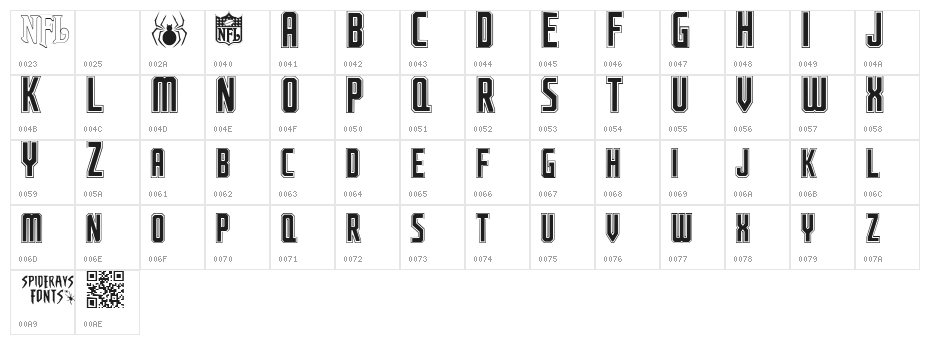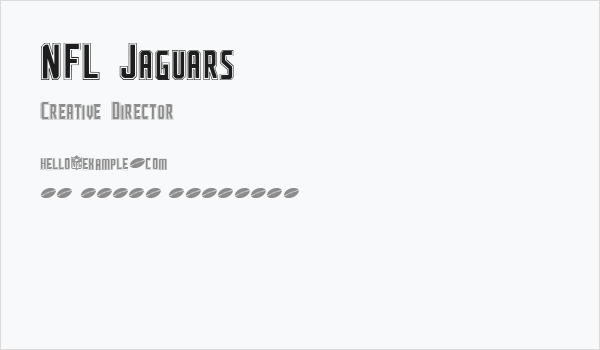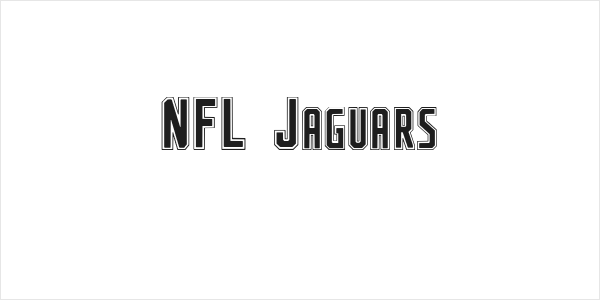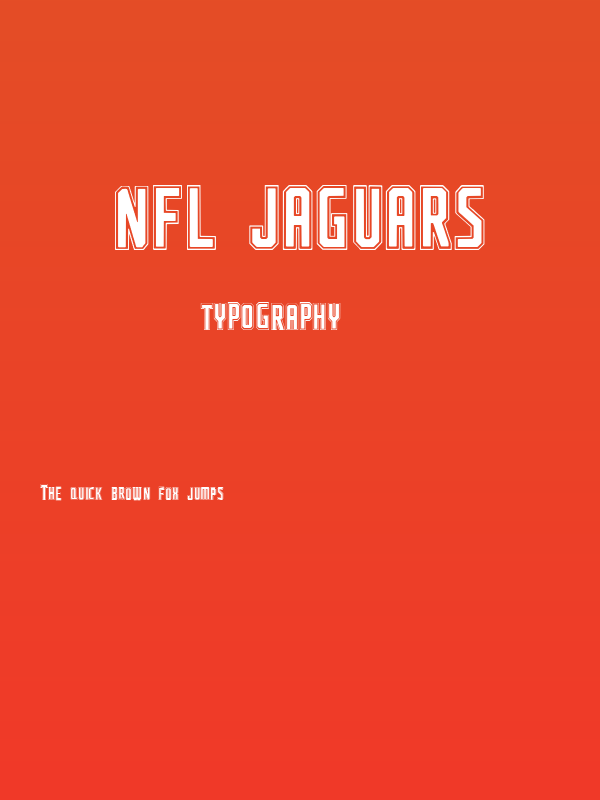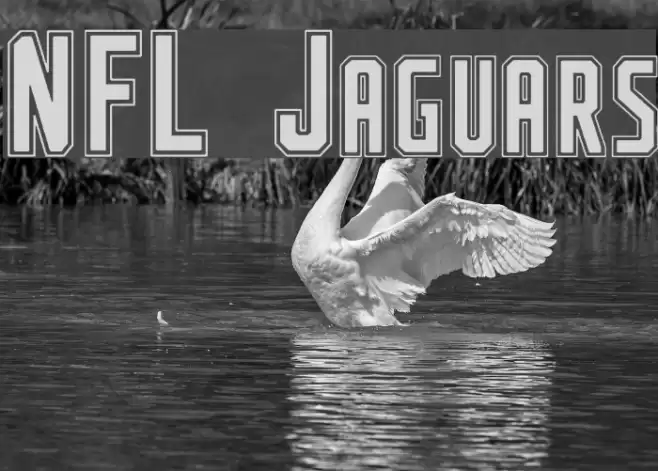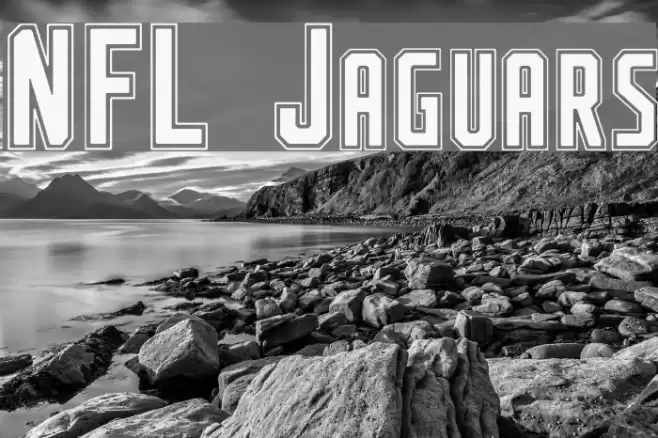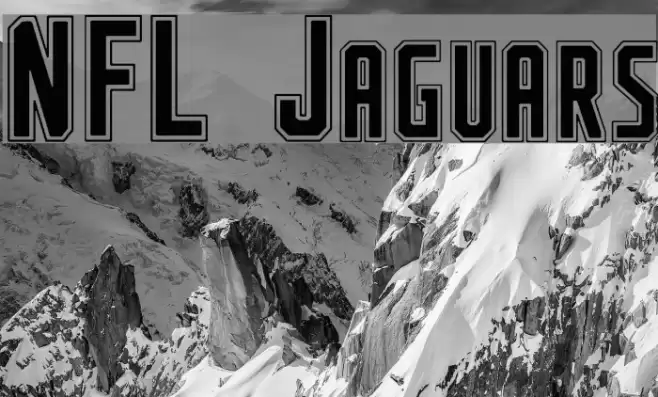
NFL Jaguars Font
| Stil general | Sporty, Collegiate |
| Caz de utilizare | Logos, Headlines, Merchandise |
| Proiecte propuse | Ideal for sports branding, team logos, merchandise, and promotional materials. |